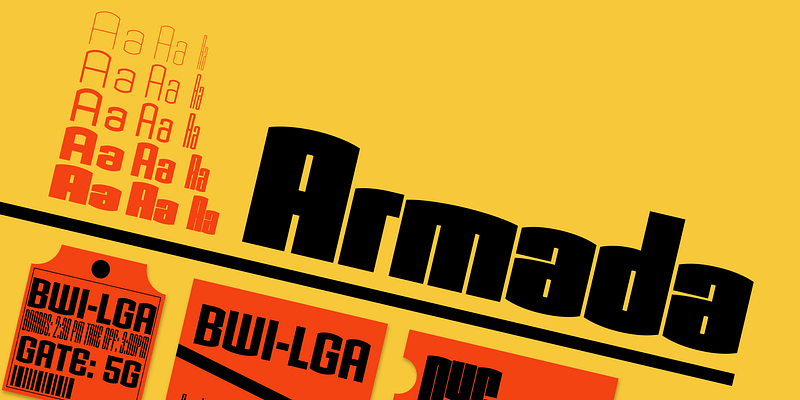
Tobias Frere-Jones는 1987년에 Armada를 시작했습니다. Armada의 실험적인 알고리즘 디자인은 19세기 미국 도시 경관의 주철 및 벽돌 구조의 건축 기하학에서 자주 볼 수 있는 수직 및 평면 아치를 가지고 있습니다. Armada의 모든 두께와 너비는 Frere-Jones가 그렸으며, 진정한 건축 테마와 규율의 모든 변형을 보여주는 놀랍도록 다양한 전체 디스플레이 시리즈를 제공합니다.